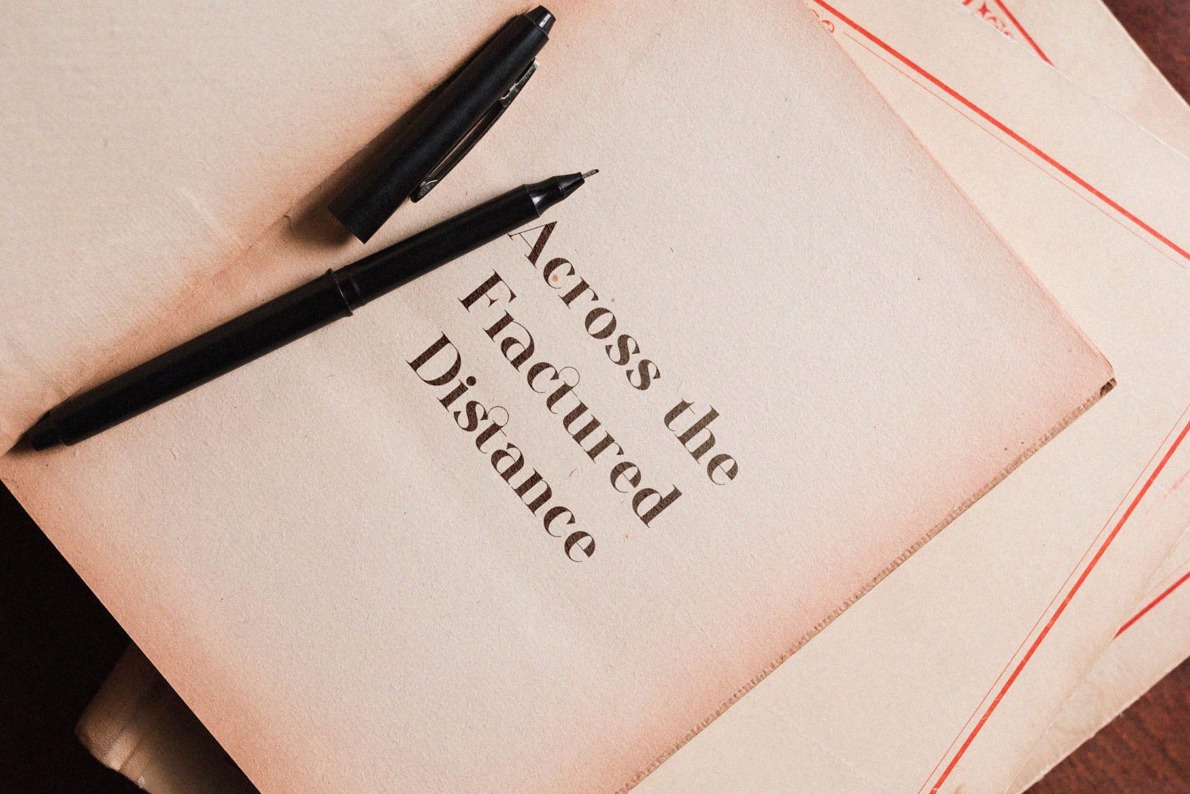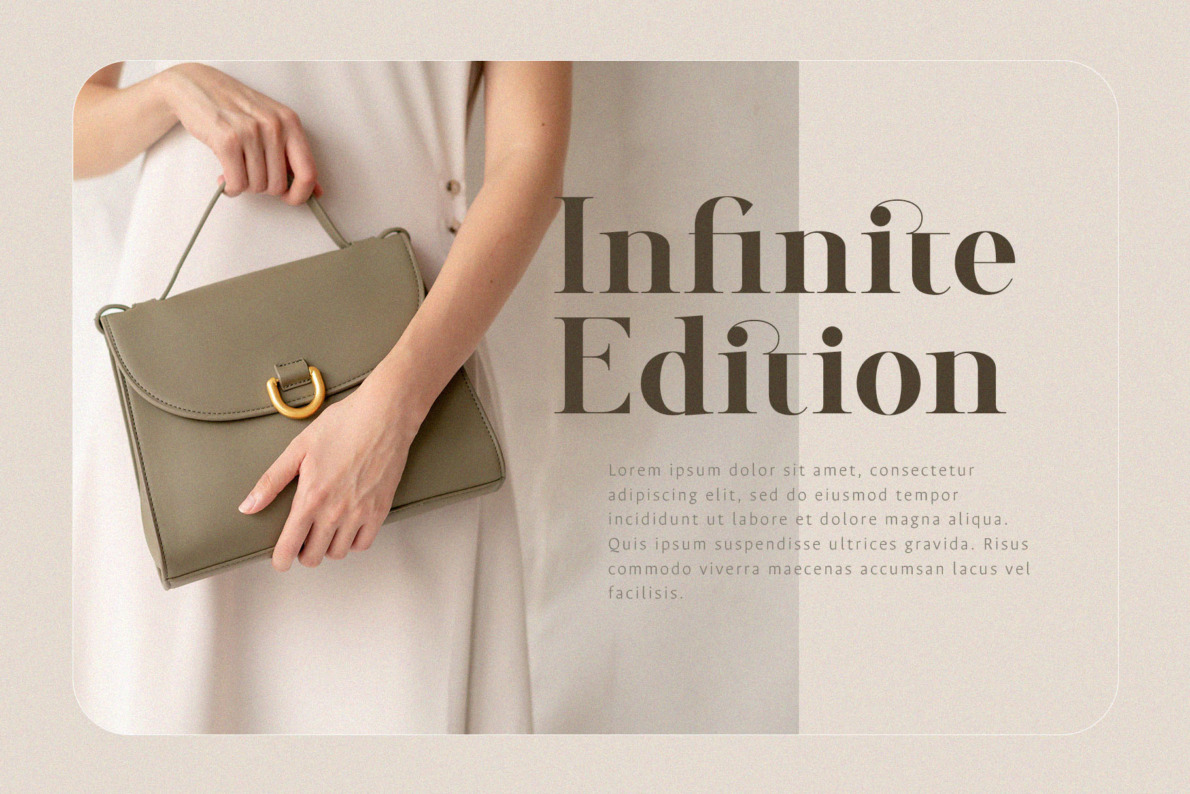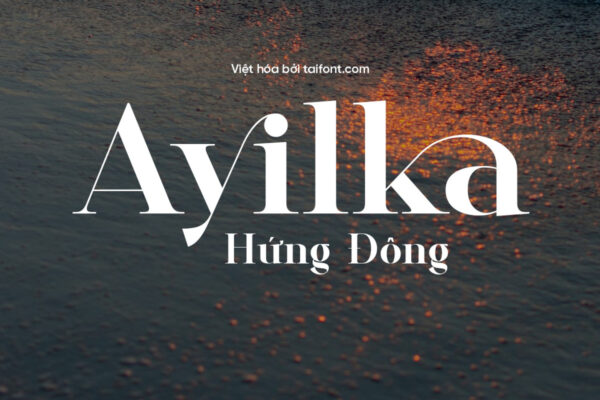
Giới thiệu về Font TF Ayilka Việt hóa
TF Ayilka Việt hóa là một font chữ có chân (serif) nổi bật với vẻ đẹp sang trọng, tinh tế và đầy phong cách. Font này được thiết kế với những đường nét thanh mảnh, duyên dáng nhưng vẫn giữ được sự rõ ràng, toát lên phong thái quý phái và đẳng cấp, lý tưởng để tạo nên sự độc đáo cho mọi thiết kế.
Với sự tinh xảo trong từng ký tự và tính thẩm mỹ vượt trội, Ayilka là lựa chọn hoàn hảo cho các ấn phẩm cần sự sang trọng và khác biệt, đặc biệt là trong các lĩnh vực:
- Thiết kế thời trang: Hoàn hảo cho các thương hiệu thời trang cao cấp, từ logo, nhãn mác sản phẩm, lookbook, đến các chiến dịch quảng bá bộ sưu tập. Font này giúp truyền tải vẻ đẹp thanh lịch, đẳng cấp và độc đáo của trang phục, nâng tầm giá trị thương hiệu.
- Thiết kế tạp chí: Lý tưởng để sử dụng cho các tiêu đề chính, lời dẫn, hoặc nội dung bài viết trong các tạp chí về thời trang, nghệ thuật, kiến trúc, hoặc lối sống. Nét chữ có chân của Ayilka giúp tăng tính trang trọng và dễ đọc, đồng thời tạo cảm giác cao cấp, thu hút độc giả.
- Thiết kế nhận diện thương hiệu: Phù hợp cho logo, tagline hoặc bộ nhận diện thương hiệu muốn truyền tải sự tinh tế, uy tín và sự thanh lịch. Ayilka giúp xây dựng một hình ảnh thương hiệu vững chắc và dễ nhận diện.
Với TF Ayilka Việt hóa, bạn có thể dễ dàng thổi hồn tinh tế, sang trọng và vẻ đẹp hoàn hảo vào các thiết kế, tạo ra những sản phẩm không chỉ đẹp mắt mà còn đầy cảm xúc và sức hút đặc biệt.